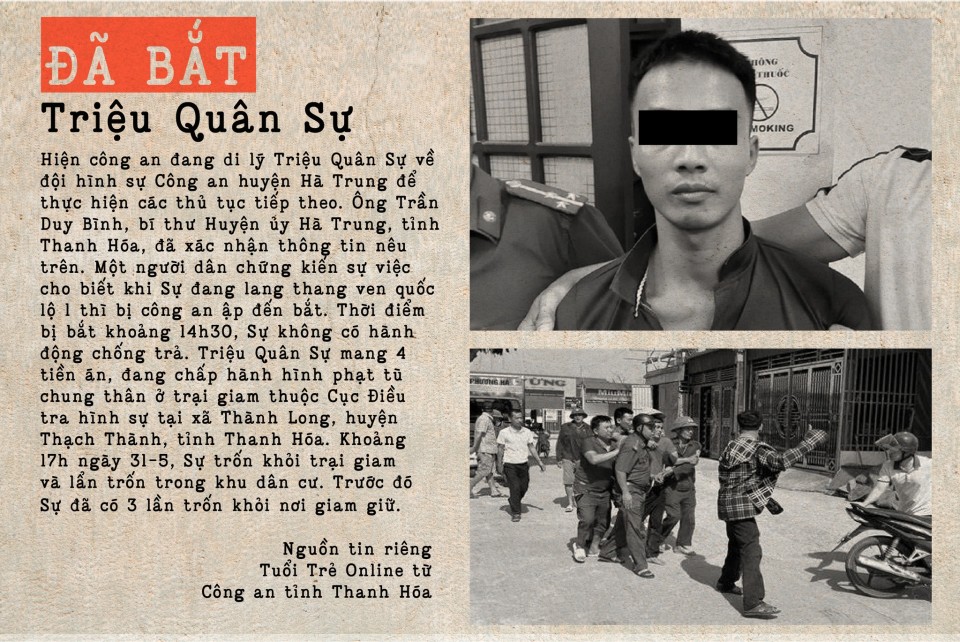
Tải Font việt hoá MJ Bygonest ( 2 font ) – Bộ Font Hoài Cổ Đẳng Cấp Cho Thiết Kế
Giới thiệu về bộ Font việt hoá MJ Bygonest ( 2 font )
Trong thế giới sáng tạo, việc lựa chọn một Font Chữ phù hợp chính là chìa khóa để truyền tải linh hồn của tác phẩm. Font việt hoá MJ Bygonest ( 2 font ) là một bộ phông chữ Serif mang đậm phong cách cổ điển, thanh lịch nhưng không kém phần hiện đại. Với đường nét được trau chuốt tỉ mỉ, bộ font này giúp các thiết kế trở nên chuyên nghiệp và có chiều sâu hơn. Việc sở hữu phiên bản việt hóa hoàn chỉnh giúp người dùng tại Việt Nam dễ dàng sử dụng trong các phần mềm thiết kế mà không lo lỗi dấu hay khoảng cách ký tự.
Đặc điểm nổi bật của MJ Bygonest
Bộ Font việt hoá MJ Bygonest ( 2 font ) bao gồm hai định dạng chính là Regular và Italic, tạo nên sự linh hoạt tối đa cho người sử dụng. Điểm nhấn của MJ Bygonest nằm ở các nét chữ có độ tương phản nhẹ, mang lại cảm giác dễ đọc và tinh tế. Đây là lựa chọn lý tưởng cho các bạn học sinh, sinh viên khi thực hiện các dự án thiết kế báo tường, bìa sách hoặc các bài thuyết trình cần sự trang trọng. Ngoài ra, tính ứng dụng của nó còn mở rộng sang các lĩnh vực như thiết kế logo, thiệp mời và nhận diện thương hiệu cao cấp.
Cách ứng dụng Font việt hoá MJ Bygonest ( 2 font ) hiệu quả
Sáng tạo cùng phong cách Vintage
Nếu bạn đang tìm kiếm một công cụ để tạo ra những sản phẩm mang hơi hướng hoài cổ của những thập niên trước, Font việt hoá MJ Bygonest ( 2 font ) chắc chắn sẽ không làm bạn thất vọng. Bạn có thể kết hợp chúng với các tông màu trầm như nâu đất, xanh rêu để tạo nên những poster hay ảnh trích dẫn đầy cảm xúc. Sự kết hợp giữa nét chữ Serif truyền thống và bảng mã tiếng Việt chuẩn giúp thông điệp của bạn trở nên gần gũi và ấn tượng hơn với người xem.